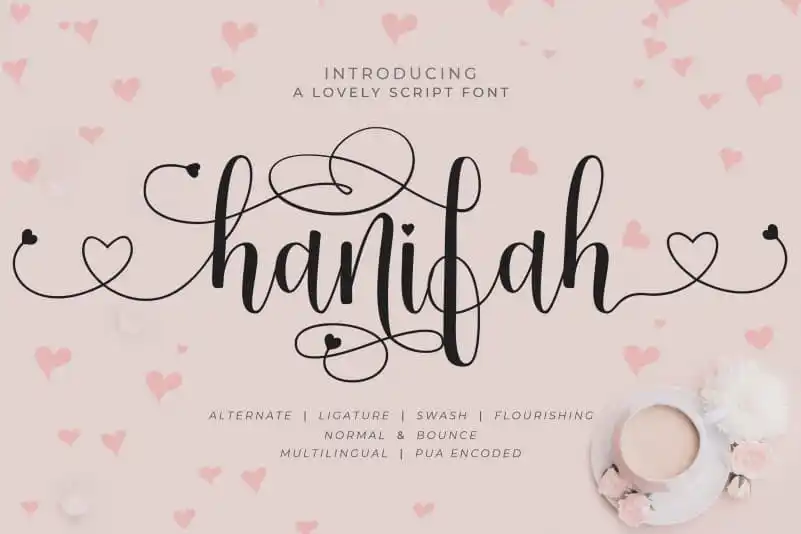
Hanifah Calligraphy Font – Download Grátis
A fonte Hanifah Calligraphy é uma escolha excepcional para quem busca um estilo script agradável e elegante. Ela se destaca pela sua composição suave de traços, repleta de detalhes sofisticados que elevam qualquer texto ao nível do luxo. Esta fonte não apenas oferece flexibilidade com suas várias opções de uso – normal, arredondada, casual ou sem cauda – mas também é versátil o suficiente para adaptar-se a diferentes contextos e ambientes, seja em cartazes publicitários ou documentos formais. Com Hanifah Calligraphy Font, você pode explorar uma variedade de opções que vão além do básico. Seja para dar um toque especial em seu texto ou criar um design único, este é um recurso indispensável para qualquer designer ou profissional de estética. Este conjunto de traços sofisticados e detalhes finos cria texturas únicas, tornando a Hanifah Calligraphy Font uma escolha inteligente para aqueles que buscam trazer personalidade e qualidade a seus projetos de design.